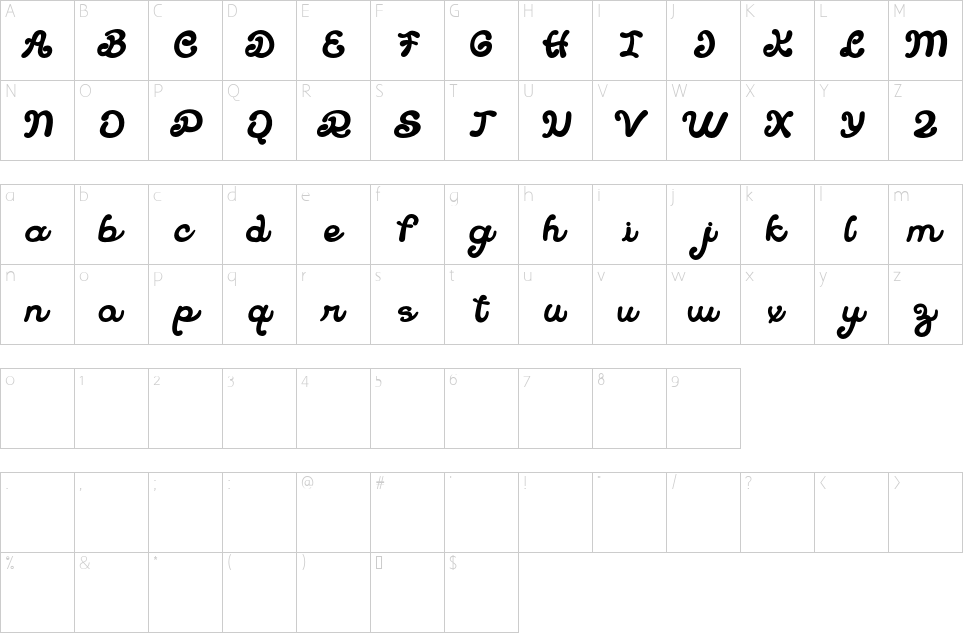
Descubra a harmonia do Glaigo Font, uma elegante escolha para designers e criadores de conteúdo que buscam expressar seu estilo único com facilidade. Esta fonte foi cuidadosamente desenvolvida pela Pandeka Studio, e sua simplicidade e precisão permitem um uso versátil em projetos variados. Nesta categoria de fontes gratuitas, o Glaigo oferece uma maneira fácil de adicionar personalidade a seus materiais digitais. Seja para criar gráficos interessantes, desenhar slogans impactantes ou formatar textos de forma minimalista, seu design suave e agradável ao olho torna a Glaigo um dos grandes nomes neste segmento. Com sua versatilidade e bom equilíbrio entre simplicidade e elegância, o Glaigo atende às necessidades do design gráfico moderno. E com apenas 254 downloads até o momento, é claro que há ainda muito potencial para explorar esta fonte de qualidade no seu portfólio. Descubra agora como a Glaigo pode transformar sua forma de expressão visual e faça parte da comunidade de criadores que se beneficiam constantemente da vasta gama de recursos disponíveis na internet.